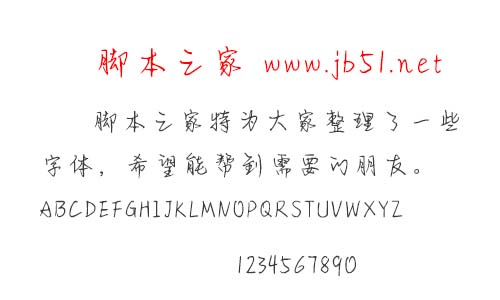
漢儀1起走到永9簡是漢儀字庫推出的一款手寫風(fēng)格藝術(shù)字體,字體筆觸較為粗實(shí),具有很好的視覺效果,適合應(yīng)用于藝術(shù)設(shè)計(jì)、平面宣傳設(shè)計(jì)、網(wǎng)頁設(shè)計(jì),書法字帖等領(lǐng)域,歡迎喜歡漢儀1起走到永9字體的朋友前來下載使用。